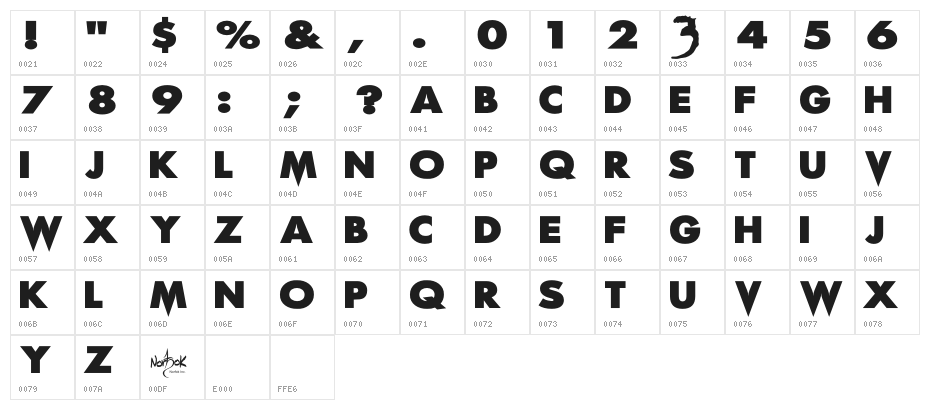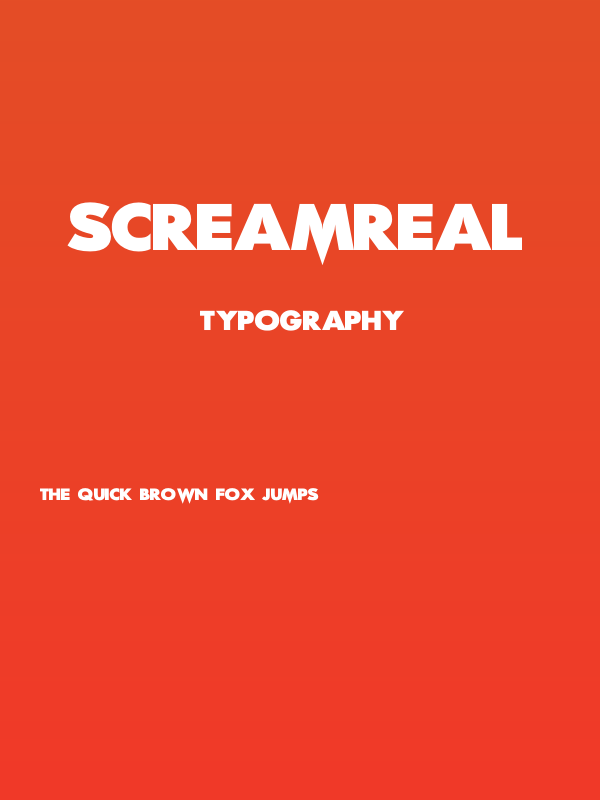
ScreamReal Font
| 全体的なスタイル | Modern, Dramatic |
| 用途 | Headlines, Posters, Logos |
| おすすめプロジェクト | Ideal for horror-themed posters, movie titles, Halloween event promotions, and any project requiring a bold, dramatic typeface. |